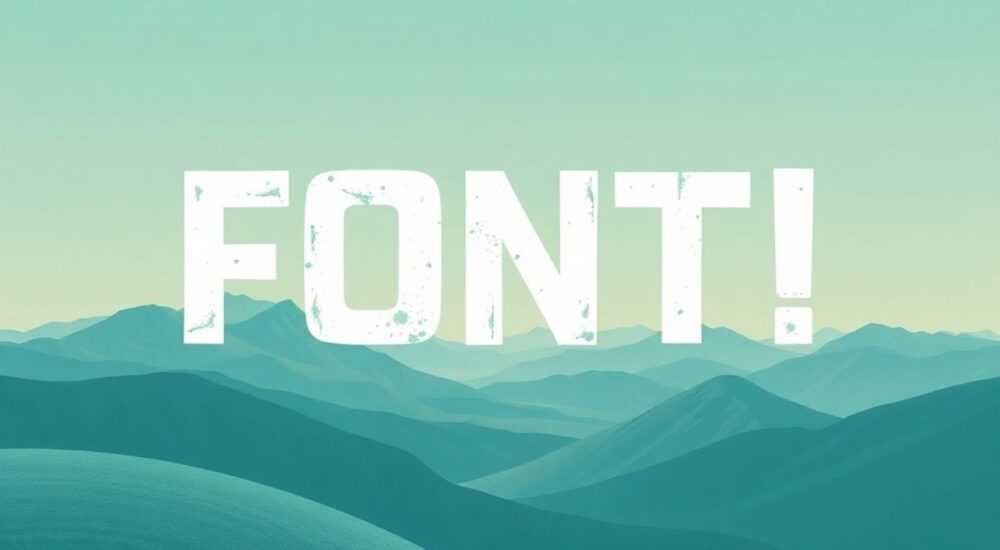
Как создать свой шрифт в фотошопе
Несмотря на популярность Photoshop как инструмента для ретуши и композитинга, многие пользователи не знают, что его можно использовать для создания собственных шрифтов — не для профессиональной типографики, но для уникальных графических проектов: логотипов, постеров, цифрового искусства и соцсетей. Photoshop не заменяет специализированные программы вроде Glyphs или FontForge, но позволяет быстро визуализировать, редактировать и экспортировать текстовые элементы в виде векторных или растровых шрифтов — идеально для дизайнеров, которые хотят выделиться стилем, не углубляясь в кодирование шрифтов.
Вы можете создать персональный шрифт в Photoshop, превратив ручные буквы в векторные формы, сохранив их как SVG или PNG-символы для последующего использования в текстовых редакторах. Для полноценного шрифта с клавишами и диакритиками используйте специализированные инструменты, но для уникальных заголовков — Photoshop идеален.
Зачем создавать свой шрифт в Photoshop
Создание уникального шрифта — это не просто модный тренд, а стратегический инструмент брендинга. По данным исследования Adobe, 67% дизайнеров используют персонализированные типографские решения в маркетинговых кампаниях, чтобы повысить узнаваемость на 30–40%. В Photoshop вы можете воплотить любую стилистику — от готического рукописного шрифта до футуристического цифрового шрифта с градиентами и текстурами, которые невозможно воспроизвести стандартными шрифтами.
Представьте, что вы создаёте постер для музыкального альбома или логотип для независимого бренда. Стандартный шрифт — это как надеть один и тот же костюм, что и все. А ваш собственный шрифт — это уникальный стиль, который становится визитной карточкой. Photoshop позволяет вам не ограничиваться предустановленными глифами, а проектировать каждый символ с нуля, контролируя каждую кривую, тень и текстуру.
Полезно знать: Даже если вы не планируете делать полноценный шрифт с 256 символами, создание 20–30 букв для заголовков уже даст вам конкурентное преимущество в визуальном контенте.
Подготовка инструментов и настроек
Перед началом работы убедитесь, что Photoshop настроен правильно. Откройте программу и создайте новый документ: размер 2000×2000 пикселей, разрешение 300 ppi, режим RGB, белый фон. Такой формат обеспечит высокое качество при масштабировании и последующем преобразовании в вектор.
Важно включить вспомогательные функции: Вид → Сетка и Вид → Привязка к сетке. Это поможет выравнивать буквы по базовой линии, высоте x и верхней/нижней границам. Также активируйте Панель «Слой» и Панель «Свойства» — они понадобятся при редактировании векторных форм.
Для рисования букв используйте инструмент Перо (P) — он даёт полный контроль над контурами. Не полагайтесь на кисти для создания основных форм — они растровые и не масштабируются. Если вы хотите начать с рукописного наброска, нарисуйте его на бумаге, отсканируйте, импортируйте в Photoshop как отдельный слой, уменьшите непрозрачность до 30% и наложите поверх него векторный контур.
Полезно знать: Используйте цветные слои для разных элементов: базовые формы — серые, детали — красные, тени — синие. Это упростит отладку и редактирование.
Проектирование букв: от наброска до вектора
Создание шрифта начинается с выбора стиля. Определитесь: будет ли это скриптовый, геометрический, моноширинный, декоративный? От этого зависит, как вы будете строить пропорции. Например, в скриптовом шрифте важна связность букв, а в моноширинном — одинаковая ширина всех символов.
Рассмотрим пошаговый процесс для буквы «А»:
1. Создайте новый слой и назовите его «A».
2. Выберите инструмент «Перо» и начните рисовать контур: левая ножка, правая ножка, поперечная перекладина.
3. Используйте точки управления для плавных изгибов — не делайте резких углов, если не задумано стилистически.
4. Закончите контур, замкнув его. Правой кнопкой → «Создать выделение».
5. Залейте выделение чёрным цветом (Ctrl+Backspace).
6. Создайте копию слоя, примените к ней «Стиль слоя → Тень» для объёма.
Повторите этот процесс для каждой буквы алфавита, цифр и знаков препинания. Начните с 10–15 символов — это уже достаточно для тестирования стиля. Сохраняйте каждый символ на отдельном слое и используйте папки (Groups) для группировки: «Буквы», «Цифры», «Знаки».
Пропорции и типографские правила
Даже в декоративных шрифтах соблюдайте базовые типографские принципы:
— Высота заглавных букв (cap height) — 70–80% от общей высоты.
— Высота строчных букв без нисходящих элементов (x-height) — 50–60%.
— Нисходящие элементы (descenders) — опускаются ниже базовой линии на 20–25%.
— Ширина символов должна быть сбалансированной: «м» шире «и», «о» — круглее «с».
Проверяйте согласованность с помощью функции Редактирование → Автоматическая привязка → Слой к слою. Это поможет выровнять все буквы по одной базовой линии.
Экспорт символов: SVG, PNG, PNG-спрайты
После завершения дизайна букв их нужно экспортировать для дальнейшего использования. Photoshop не создаёт настоящие шрифты (.ttf, .otf), но позволяет экспортировать символы в форматах, которые подойдут для генераторов шрифтов.